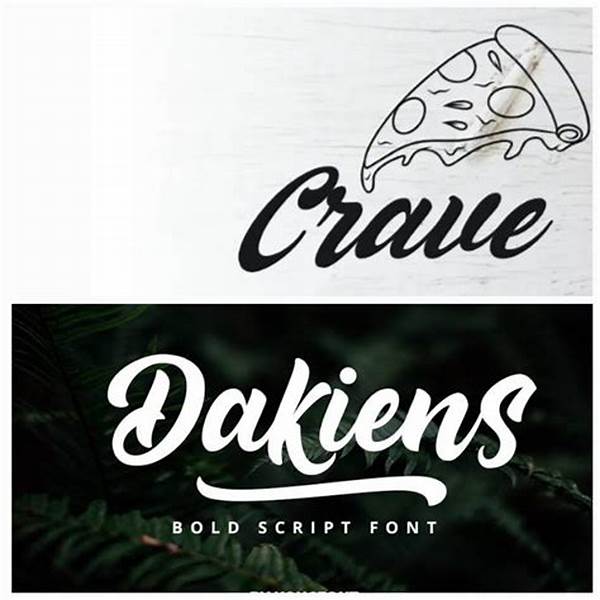
Kamu pasti setuju, ‘kan, kalau logo adalah wajah dari merek bisnis kita? Saat memulai usaha, salah satu elemen terpenting adalah merancang logo yang mencerminkan identitas dan nilai perusahaan. Salah satu cara untuk membuat logo bisnis yang menonjol adalah dengan melakukan kustomisasi font. Ya, memilih dan merancang huruf yang tepat bisa membuat logo kita berbicara lebih lantang! Nah, mari kita bahas lebih lanjut mengenai kustomisasi font ini.
Mengapa Kustomisasi Font untuk Logo Bisnis Penting?
Tentu, memilih font yang tepat bukanlah sekadar memilih huruf yang terlihat lucu atau keren. Ini lebih dari itu! Kustomisasi font untuk logo bisnis adalah tentang menciptakan sebuah nuansa yang sesuai dengan brand kita. Misalnya, jika bisnismu adalah butik fashion mewah, kita mungkin ingin menggunakan font dengan gaya elegan dan bersih. Sementara untuk bisnis startup teknologi, font dengan tampilan modern dan futuristik bisa jadi pilihan, bukan? Jadi, ketika orang melihat logomu, mereka sudah mendapatkan insting awal tentang jenis bisnismu. Melalui kustomisasi font, kita bisa membedakan diri dari pesaing dan membantu pelanggan mengingat kita lebih baik. Dalam dunia bisnis yang kompetitif ini, memiliki keunikan dan daya ingat yang kuat menjadi kunci kesuksesan, kan?
Tidak hanya itu, font yang kita pilih juga berperan dalam membangun persepsi konsumen. Dengan kustomisasi font, logo bisa menyampaikan pesan emosional yang penting. Misalnya, font yang lebih bulat dan lembut mungkin mengesankan kehangatan dan keramahan, sedangkan font yang tajam dan tegas menandakan kekuatan dan profesionalisme. Dengan kata lain, kustomisasi font untuk logo bisnis adalah tentang menciptakan perasaan yang tepat dan memastikan bahwa pesan tersebut sampai ke target audiens kita.
Dan hei, mari kita tidak melupakan aspek teknisnya. Kustomisasi font untuk logo juga memungkinkan kita untuk memastikan bahwa ukuran dan bentuk font bekerja dengan baik di berbagai platform, dari kartu nama hingga banner digital. Membangun kesan profesional dan kohesif pada semua platform inilah yang akan membentuk citra merek yang solid. Jadi, pastikan kita meluangkan waktu untuk memikirkan hal ini, ya!
Langkah-Langkah Kustomisasi Font untuk Logo Bisnis
1. Kenali Merek Kamu
Sebelum mulai, kenali dulu identitas bisnismu! Apa nilai-nilai yang ingin disampaikan? Dengan begitu, kustomisasi font untuk logo bisnis bisa lebih terarah.
2. Pilih Gaya yang Sesuai
Tentukan apakah kamu ingin gaya yang modern, vintage, atau playful? Pilihan ini akan memengaruhi keseluruhan desain logomu.
3. Eksplorasi Kombinasi Font
Jangan takut untuk bereksperimen! Kadang kombinasi dari dua atau tiga font bisa menciptakan efek visual yang menakjubkan. Kustomisasi font untuk logo bisnis bukanlah pekerjaan sekali jadi.
4. Perhatikan Keterbacaan
Pastikan font yang dipilih tetap mudah dibaca, ya! Percuma punya desain keren kalau tidak bisa dibaca dengan jelas.
5. Uji di Berbagai Media
Tes desainmu di berbagai ukuran dan media. Kustomisasi font untuk logo bisnis harus terlihat bagus di mana pun ia digunakan.
Kustomisasi Font untuk Logo Bisnis yang Efektif
Keberhasilan sebuah kustomisasi font untuk logo bisnis terletak pada seberapa baik font tersebut dapat menggambarkan esensi brand. Pastikan font yang kita pilih mencerminkan karakter bisnis. Misalnya, sebuah bisnis mainan anak-anak tentu akan memilih font yang ceria dan penuh warna. Sementara itu, firma hukum mungkin akan lebih mengutamakan font yang formal dan tegas. Menghubungkan antara elemen emosional dengan visual adalah kunci untuk mendesain logo yang efektif.
Kustomisasi font juga memberi kita semacam “lisensi” untuk bermain dan berinovasi. Tidak ada batasan sejauh kita dapat menginterpretasikan font asalkan tetap memperhatikan filosofi brand. Jika perlu, jangan segan untuk berkonsultasi dengan desainer profesional yang berpengalaman dalam kustomisasi font. Mereka bisa memberikan wawasan dan solusi kreatif yang mungkin belum terpikirkan sebelumnya. Dan jangan lupakan uji coba, ya! Lakukan riset pasar kecil untuk melihat reaksi orang-orang sebelum benar-benar meluncurkan logo baru.
Memahami Audiens: Kunci dalam Kustomisasi Font untuk Logo Bisnis
Sebelum memulai proyek kustomisasi font, penting untuk memahami siapa audiens kita. Logo yang tampaknya sempurna di mata kita belum tentu memberikan dampak yang sama pada audiens. Jika target pasar kita adalah anak muda, maka gunakan font yang energik dan dinamis untuk menarik perhatian mereka. Namun, untuk segmen korporat, sebaiknya gunakan font yang lebih serius dan profesional.
Dengan memahami audiens, kita dapat menciptakan kustomisasi font untuk logo bisnis yang lebih tepat sasaran. Proses ini juga menghindarkan kita dari kesalahan desain yang mungkin tidak sesuai dengan selera pasar. Jadi, coba deh, sesekali lakukan survei atau pengumpulan data dari target audiens, agar kita lebih memahami preferensi mereka.
Tips Memilih Font untuk Kustomisasi Logo Bisnis
1. Cocokkan dengan Brand Identity
Font harus selaras dengan identitas brand.
2. Keterbacaan adalah Kunci
Jangan mengorbankan keterbacaan demi gaya.
3. Gunakan Kontras dengan Bijak
Kontras dapat membuat font lebih menonjol, tetapi jangan berlebihan, ya!
Sekarang, saatnya kita mengambil langkah ini dan memberikan merek kita identitas yang unik dan menarik. Kustomisasi font untuk logo bisnis bukan cuma soal estetika, tapi juga tentang menciptakan hubungan emosional dengan audiens kita, memastikan bahwa bisnis kita dikenali dengan kesan pertama yang tepat. So, sudah siap mengubah wajah bisnis dengan kustomisasi font yang beda?